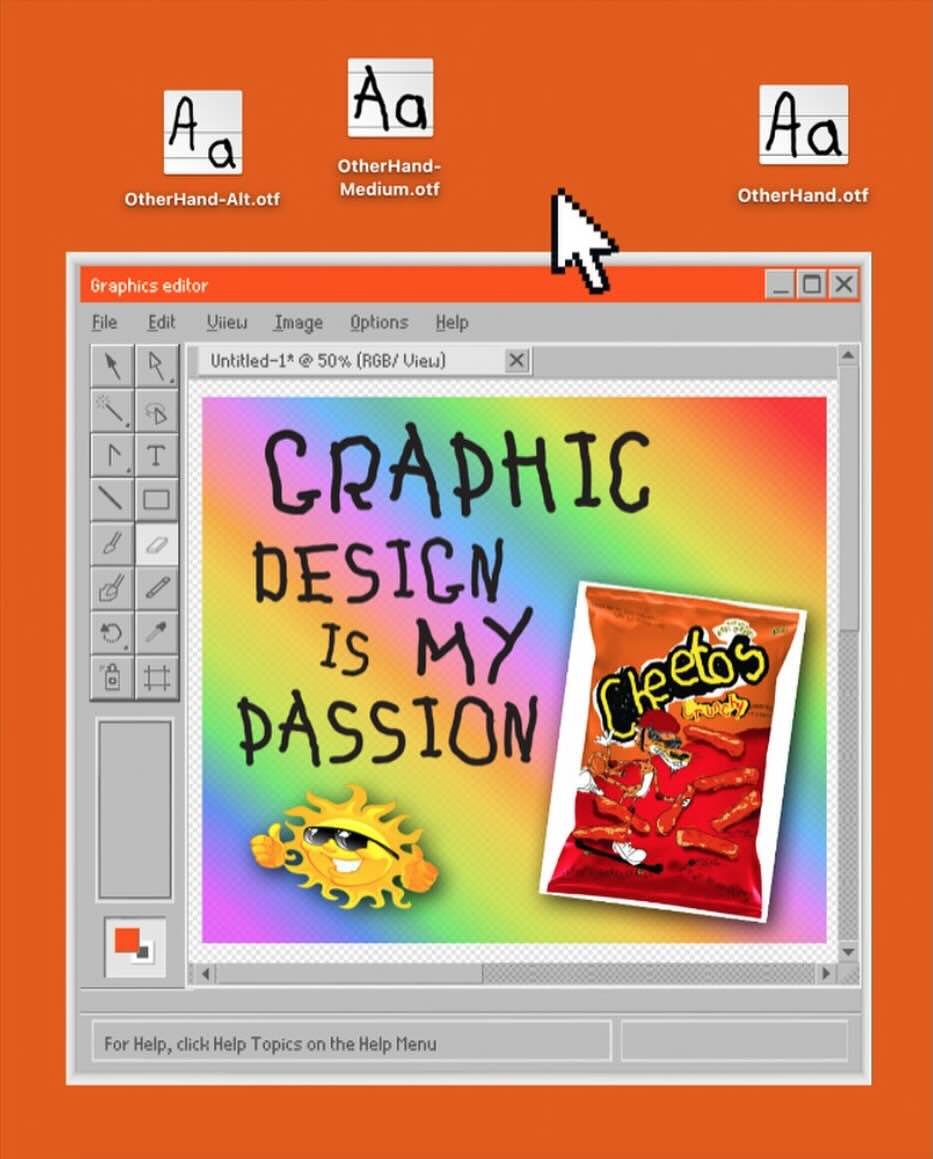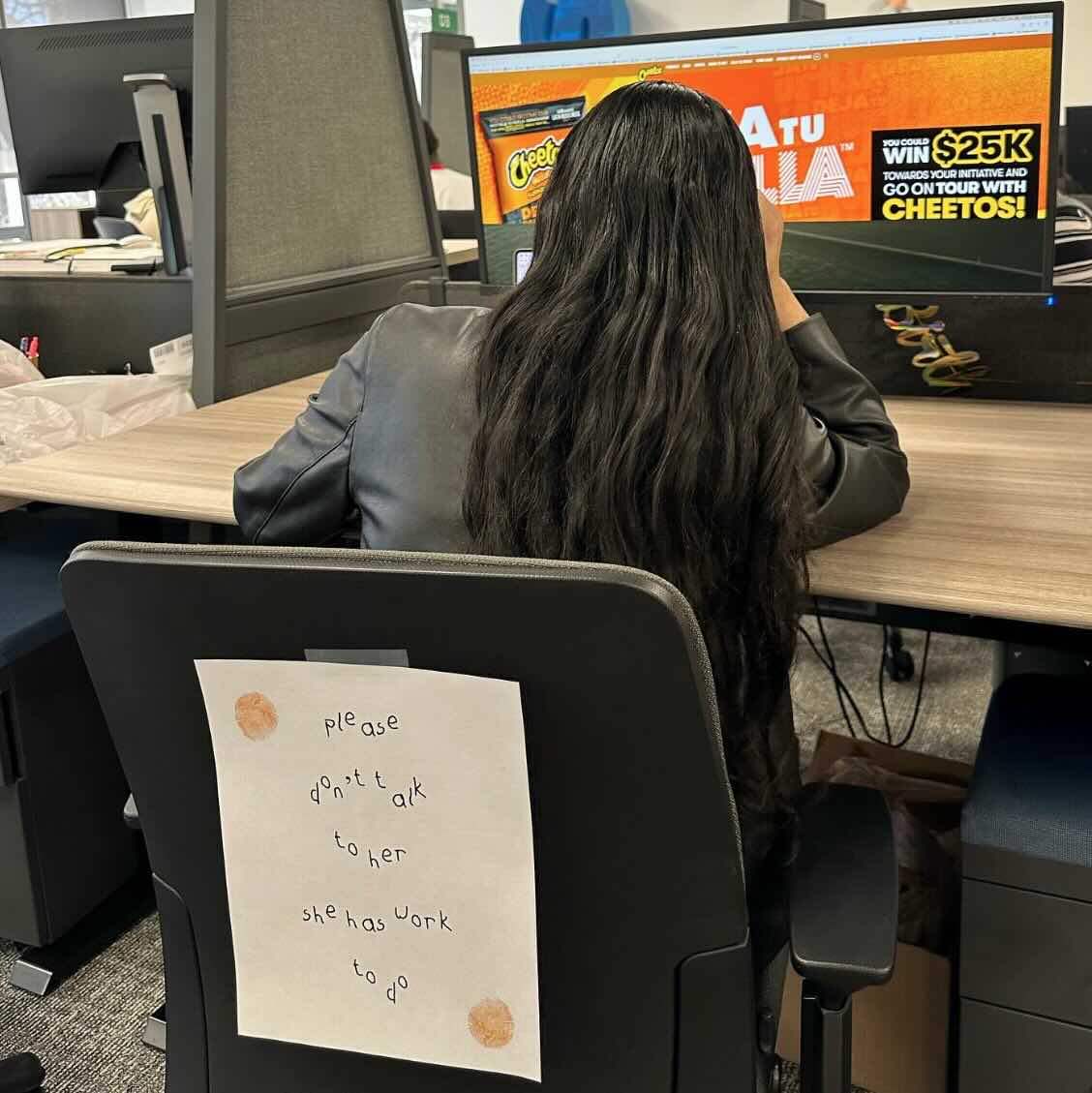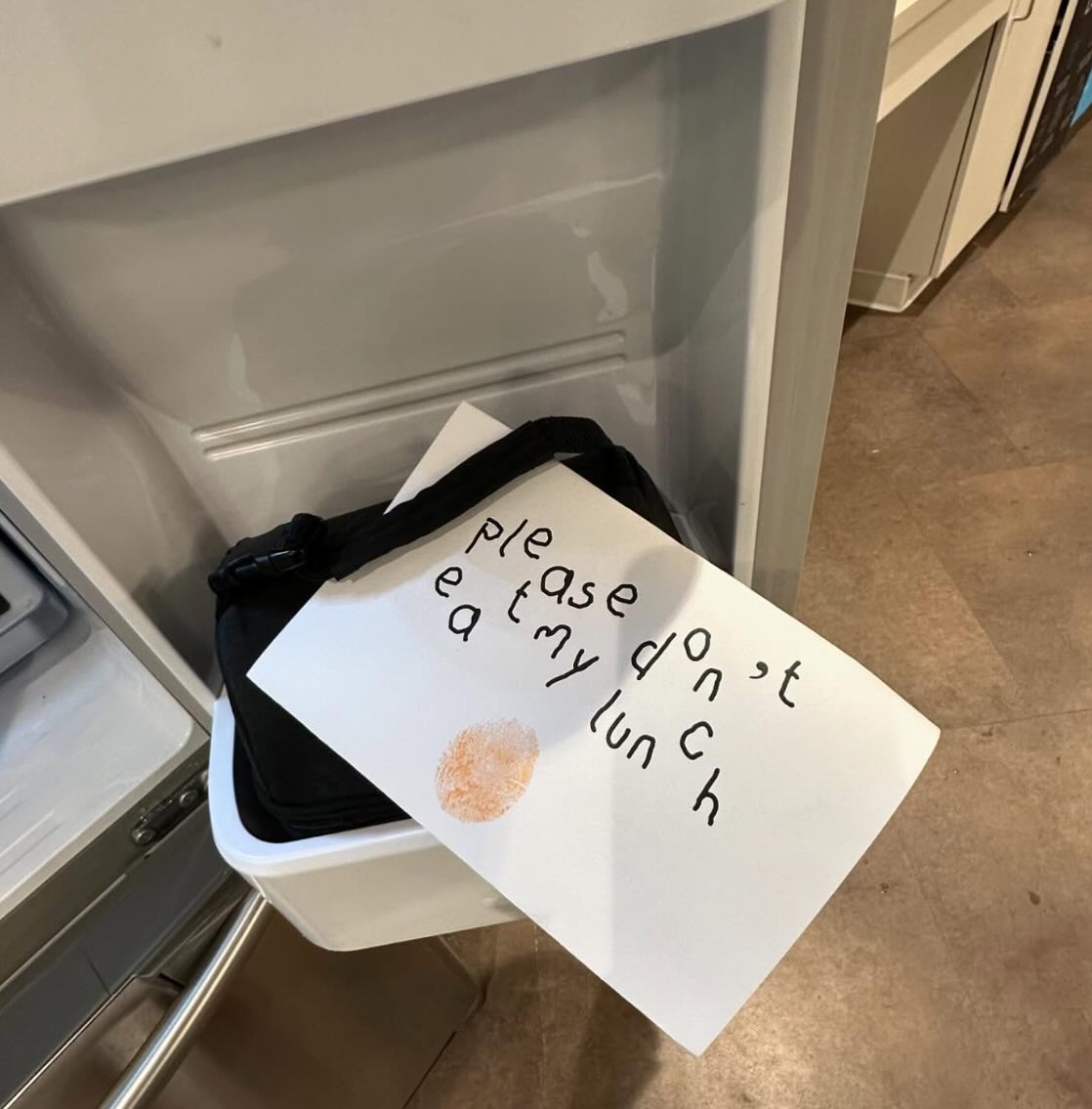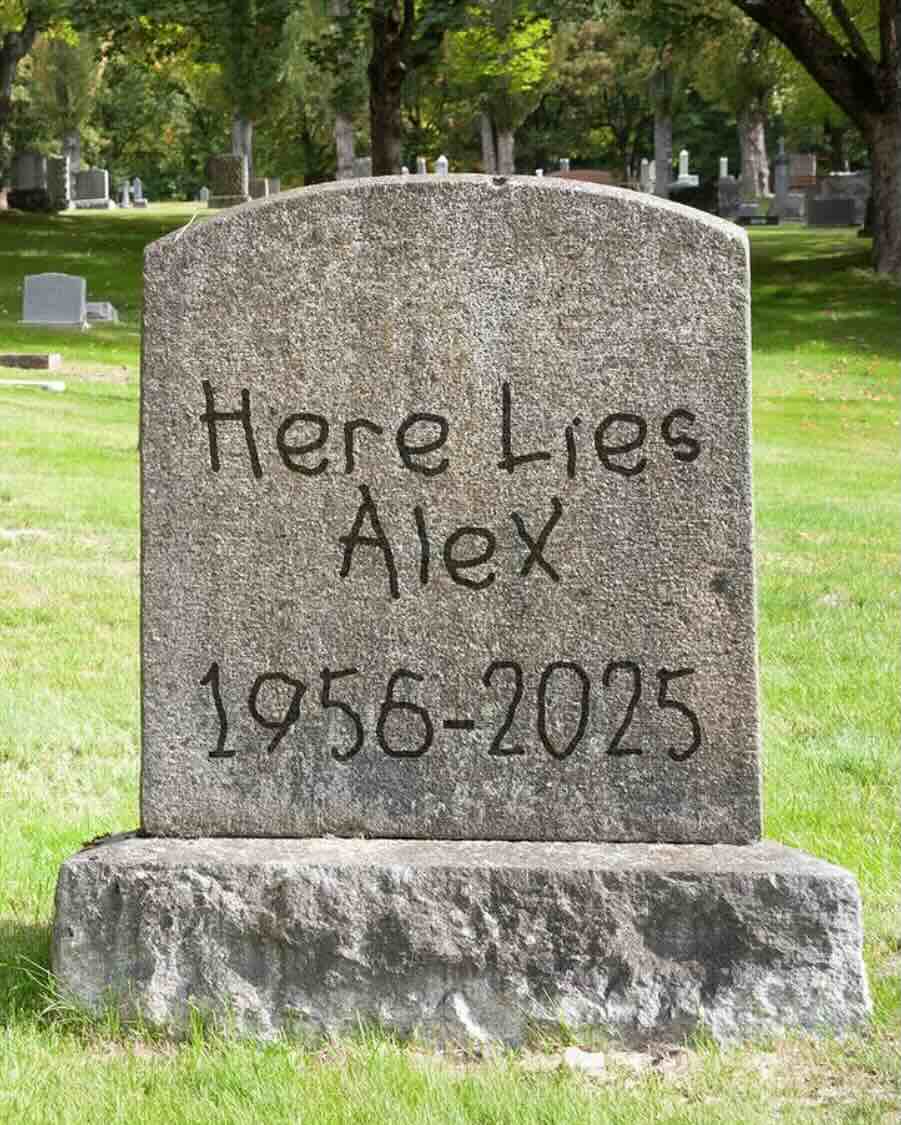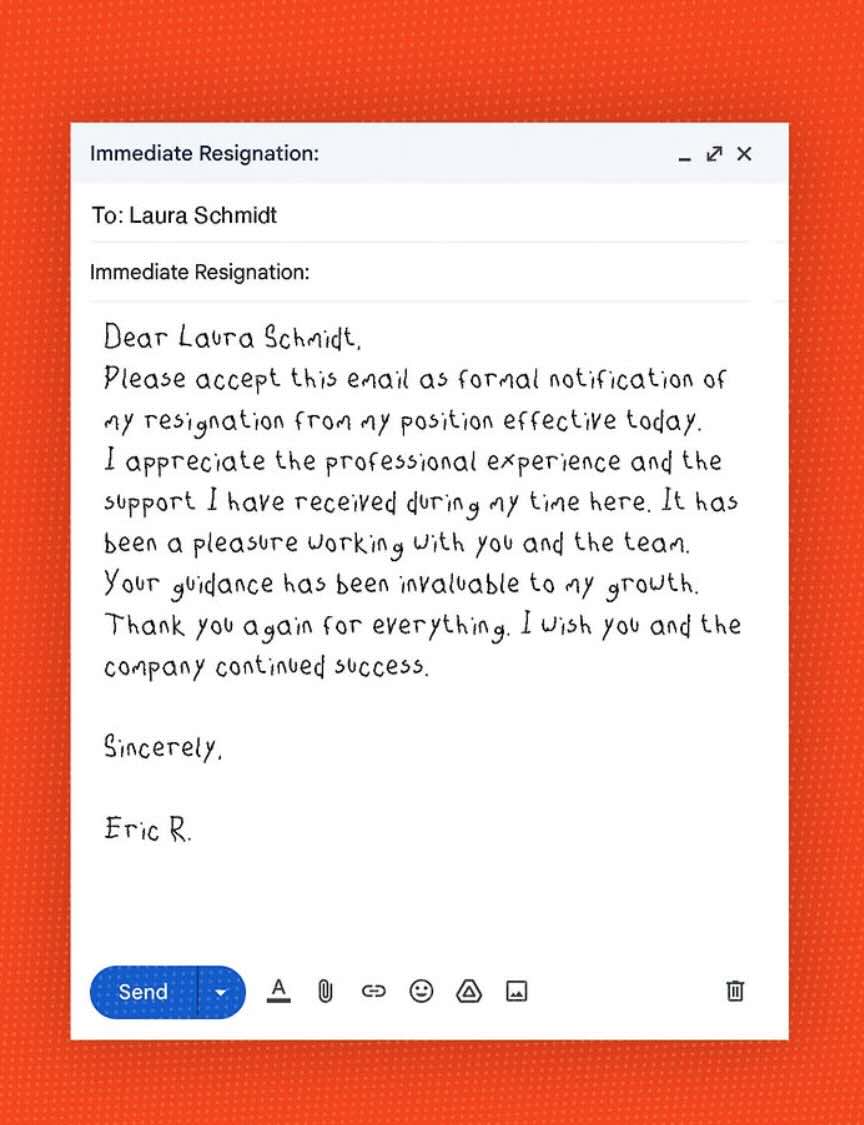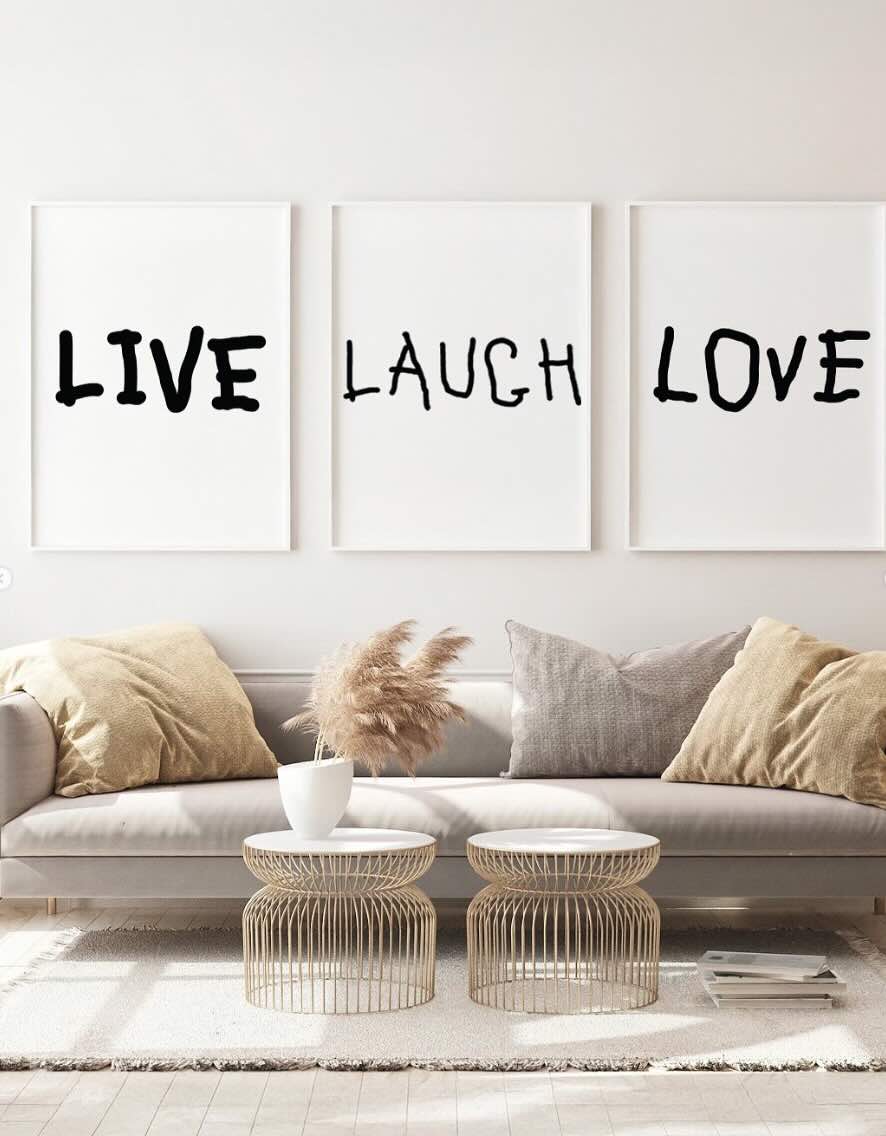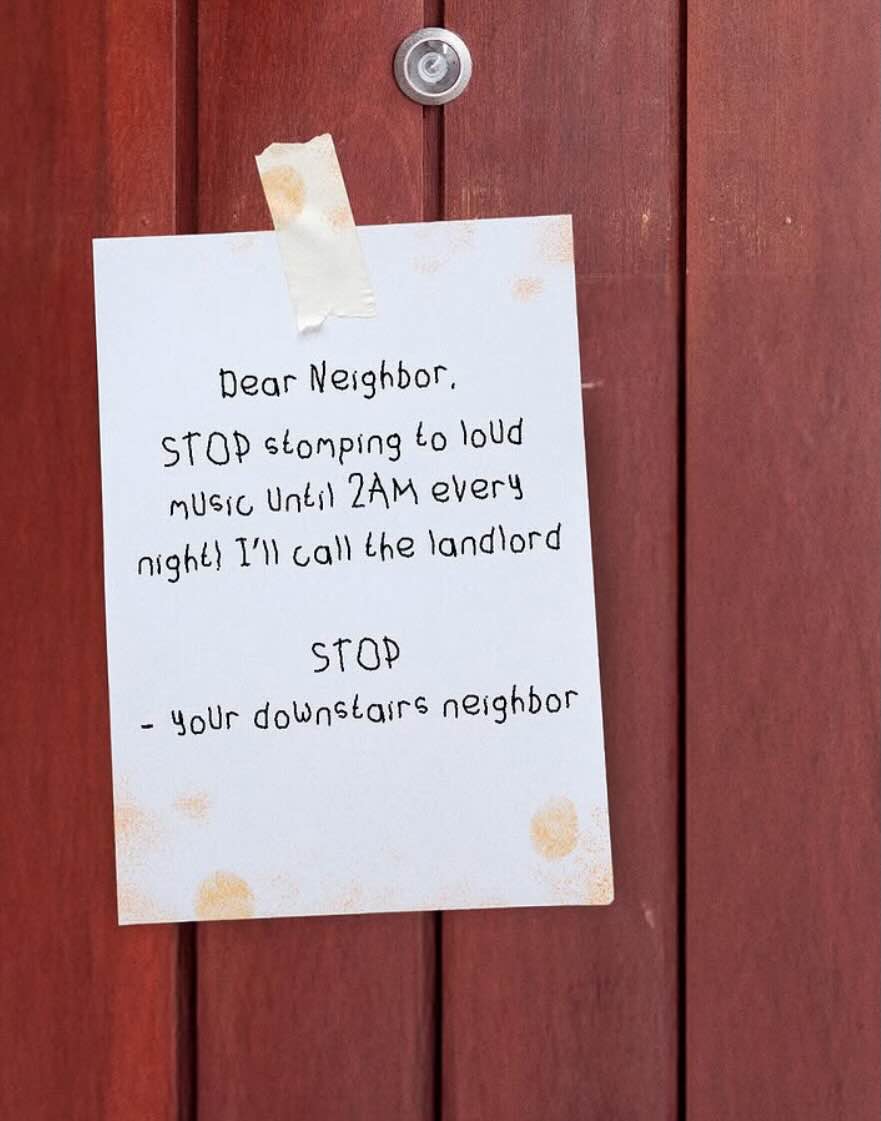
Cheetos ahonda en la pasión por su producto con una tipografía hecha con la otra mano
• La marca explora cómo sería trabajar con la mano dominante impregnada del polvo que desprenden sus snacks
• “The other hand font” ha sido diseñada por el equipo de la agencia creativa Goodby Silverstein & Partners
La mayoría de la gente suele disfrutar de sus snacks favoritos utilizando su mano dominante, lo que deja a las personas incapaces para realizar ciertas acciones. En el caso de los diseñadores, con problemas para realizar sus ideas, tal y como refleja la nueva acción de marketing de Cheetos, con la que la marca demuestra, una vez más, el amor de los consumidores por su producto.
Cheetos ha creado “The other hand font”, una tipografía creada con la mano menos dominante, ya que la principal está demasiado ocupada cogiendo snacks e impregnada del delicioso polvo que desprenden. Lo ha hecho en colaboración con la agencia creativa Goodby Silverstein & Partners y en el marco del Día Mundial de la Escritura a Mano, celebrado el 23 de enero. Concretamente, Rich Silverstein, Fundador de la agencia  ha diseñado la fuente al equipo creativo.
Así, anunciante y agencia han creado una tipografía diseñada en su totalidad utilizando la mano no dominante de los diseñadores. Se trata de una iniciativa que forma parte de la campaña "The Other Hand", con la que la marca ha destacado las cosas que les ocurren a los amantes de Cheetos cuando optan por vivir la vida con su mano dominante siempre cubierta del polvo de los cheetos.
Lejos de ser un mero ejercicio de comunicación, Cheetos ha puesto la tipografía creada a disposición de los usuarios, que pueden descargarla en la página web de la marca. La marca invita a los fans a probarla en lugares inesperados, desde el trabajo hasta el estudio, y ofrece a aquellos que publiquen los usos más atrevidos y traviesos en las redes sociales la oportunidad de hacerse con una bolsa de Cheetos de edición limitada inspirada en la fuente The Other Hand.
Además, como parte de la campaña se ha creado una extensión para los navegadores que transforman su fuente habitual en The other hand font.
“La belleza de la campaña es que celebra una verdad humana muy real: la mayoría de las personas usan su dominante para comer Cheetos, lo que significa que tienen que hacer básicamente todo lo demás en la vida usando su otra mano"; ha comentado Chris Bellinger, Director Creativo de PepsiCo Foods Estados Unidos. "Este último truco de presentar una fuente hilarantemente mala continúa mostrando las consecuencias traviesas de comer Cheetos”.
“El diseño es la forma más pura de expresión de una marca y esta fuente representa a Cheetos como nada que pudiéramos haber imaginado", ha comentado, por su parte, Rich Silverstein. "Es un testimonio de las incontables horas dedicadas a crear cada detalle. Hacerlo todo con nuestra mano no dominante fue una experiencia que nunca olvidaremos”.
Además de la pieza audiovisual principal, que muestra a los diseñadores durante el supuesto proceso creativo, la marca ha promocionado la tipografía con varias publicaciones en redes sociales que, desde el humor, exponen posibles aplicaciones. Así, ha compartido tanto memes, como imágenes de la tipografía en el entorno laboral.